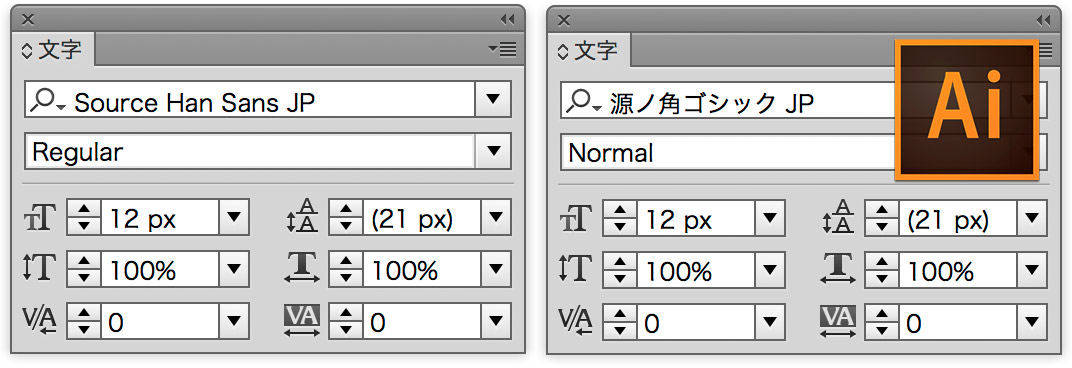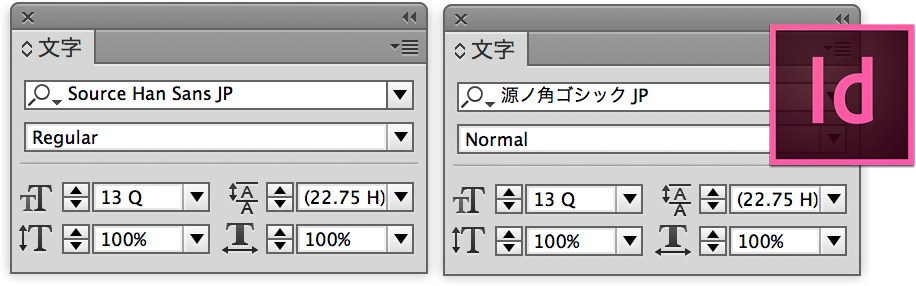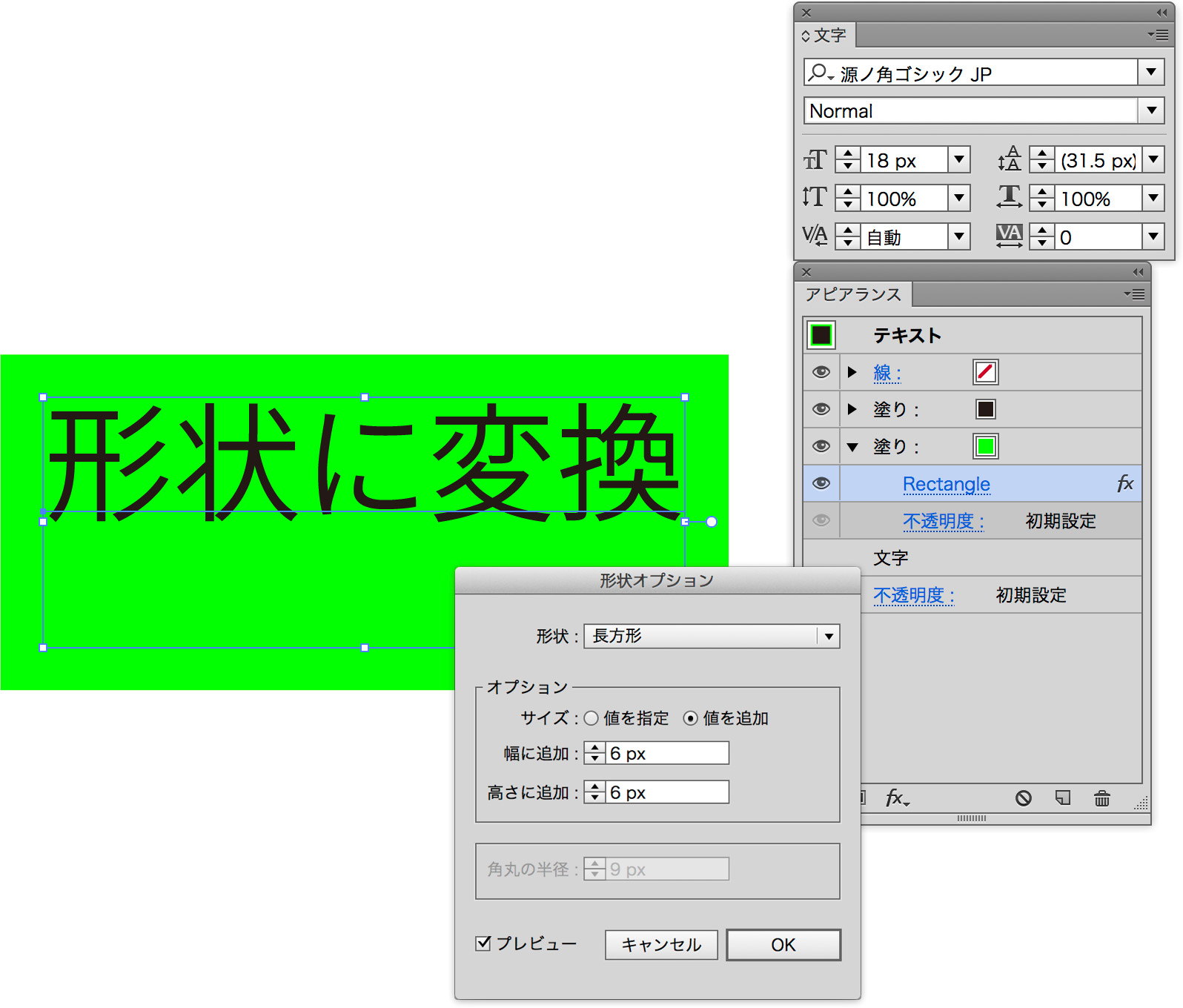
Source Han Sans(源ノ角ゴシック)/Noto Sansがリリースされました
2014年7月15日、Source Han Sans(Noto Sans)というオープンソースフォントファミリーがリリースされました。7つのウエイトが用意されている高品位なフォントです。
ややこしいリリース体系
これまでのフォントに関する常識と異なる部分が多く、ちょっとややこしい感じです。
- アドビとGoogleからリリースされている。アドビからリリースされているものは「Source Han Sans」、Googleからリリースされているものは「Noto Sans」のように呼び方が異なる
- アドビからリリースされている「Source Han Sans」には、「マルチ言語版」、「単言語版」、「OTC版」、「TypeKit版」の4つがある。
- ダウンロードした単言語版は、Illustrator/InDesignの[文字]パネルでは「源ノ角ゴシック」(ゲンノカクゴシック)と表示される。Typekitで同期したものは「Source Han Sans JP」と表示される。これらは共存できない
▼Illustratorの[文字]パネル
▼InDesignの[文字]パネル
ウエイト名
ややこしいことに、フォントによってウエイト名が異なります。
開発
Google、アドビ、および、Changzhou SinoType Technology、イワタ、そして Sandoll Communicationなどのフォントメーカーとの協力によって開発されたそうです。
Robotoとの調和
Noto Sansの欧文部分には、Androidの標準フォントであるRobotoが使われていると書かれていることがありますが、それは誤りで、Source Han Sans、Noto Sansともに、同じ欧文を使っています。
Robotoとの調和を意識して開発されており、組み替えたサンプルが掲載されていると思われます。
Robotoフォントは、リデザインされたものがリリースされたとありますが、現在ダウンロードできるバージョン(1.2)は、リデザイン前のもののようです。
Noto?能登?
Notoは「No 豆腐」に由来するそうです。つまり、「豆腐」(コンピューターで文字が表示されないときに表示される四角形)を排除する、という意味合いとのこと。
「源ノ角ゴシック」はなんて読むの?
「源ノ角ゴシック」は「ゲンノカクゴシック」と読むそうです。
DTPではどれを使えばいいの?
要点を抜き出すと…
- DTPでは「単言語版だけを使う」のがベスト
- TypeKit版はInDesign CS5以降のパッケージでフォント収集されない(ダウンロード版は収集される)
- 全角ダーシを2つ並べると2倍ダーシ専用の合字字形になる(ただし、U+2015を禁則処理セットの分離禁止文字に追加する必要アリ)
DTPでの注意点
Illustratorで源ノ角ゴシック(Source Han Sans/Noto Sans)を使って入力すると、バウンディングボックスが(改行でもされているように)大きく表示されます。
そのため、アウトラインをかけずに[形状に変換]を行うと、次のサンプルのように、とても大きな図形になってしまいます。
[オブジェクト]メニューの[アートボード]→[オブジェクト全体に合わせる](または[選択オブジェクトに合わせる])を実行しても、下に余白が生じてしまってとても不便です。
個人的な感想
- 「りょう」に似てるな〜と思ったら、西塚涼子さんがデザインされていました。
- 第一印象、「ら」と「り」が大きい…と思いました。しかし、「スモールデバイスで読みやすい、すっきりとしたデザイン」というデザインコンセプトによって開発されているとのことで、スモールデバイスではよいバランスなのかもしれません(要検証)。
なお、スモールデバイスへの対応だけでなく、黒バックに白文字で使われることも意識されているようです。